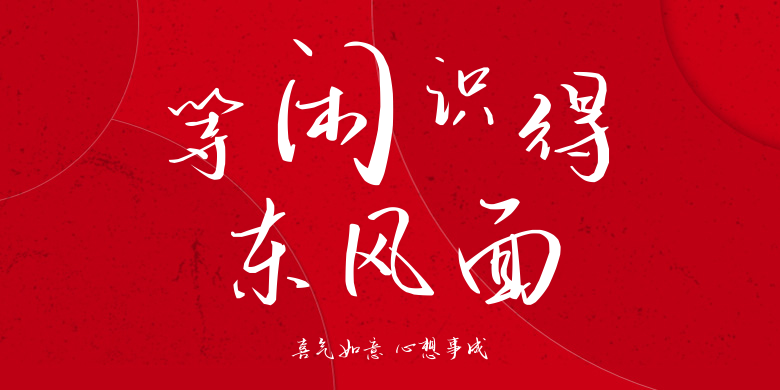
喜气如意 心想事成
喜气如意 心想事成,这款字体结构工整、笔画清晰,兼顾美观与易读性,适用于标题、正文、海报、包装、LOGO 等多种场景。字形优雅稳定,风格百搭耐看,适配日常排版与创意设计,让文字呈现更舒适、更具质感。喜气如意 心想事成一笔一画,皆是细节,以均衡的比例、流畅的线条打造舒适视觉体验,字形端正大气,风格简约现代。无论是商业设计、品牌宣传还是日常排版,都能轻松驾驭,让文字更有格调与力量。喜气如意 心想事成字体下载。